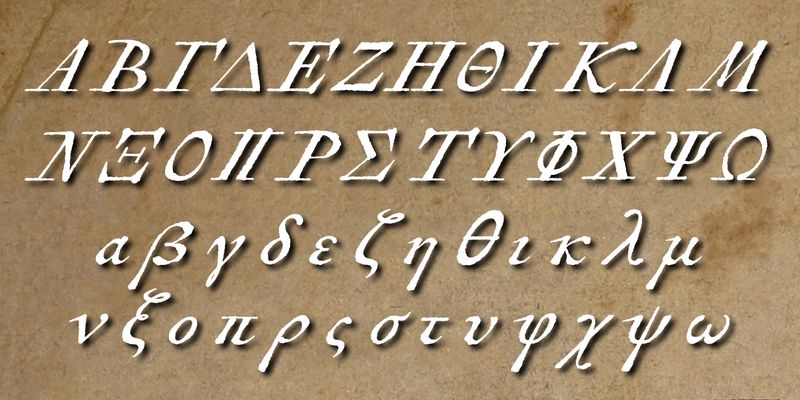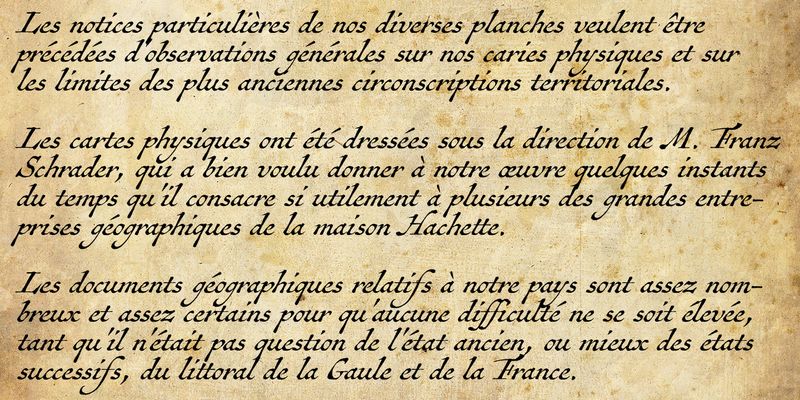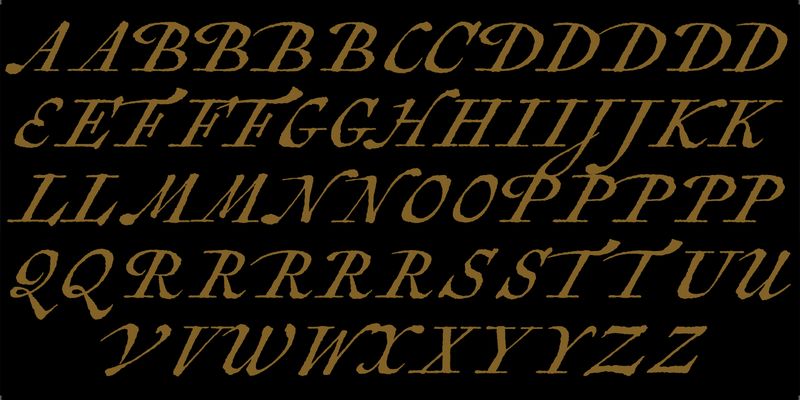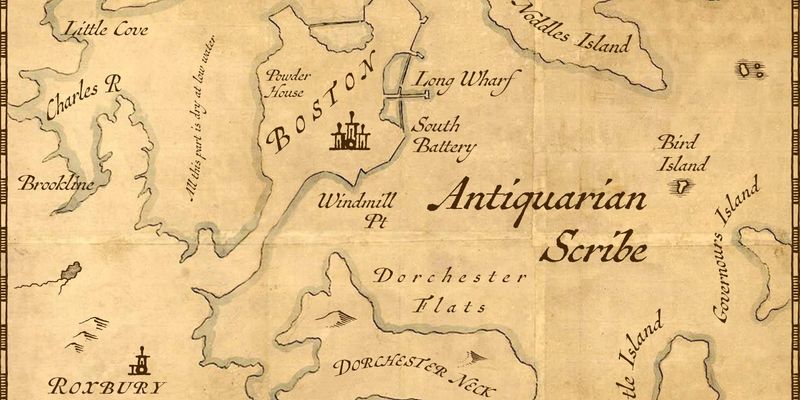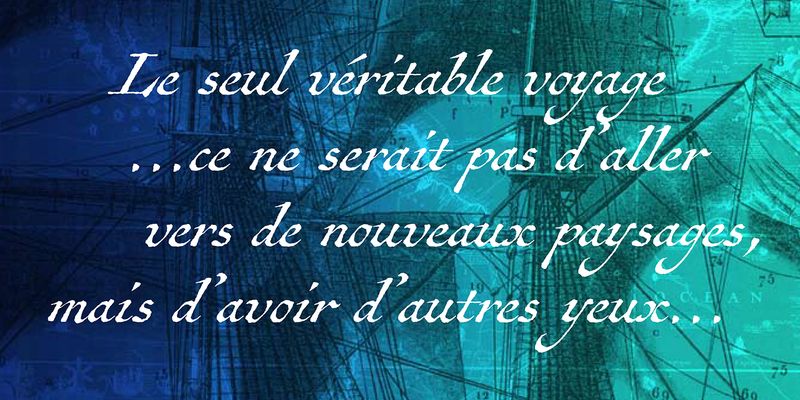
Antiquarian Scribe™ simuliert den handgeschriebenen Text im Atlas Historique von Henri Abraham Chatelain aus dem 18. Verfügt über mehr als 1.000 Glyphen, darunter vollständige lateinische Schriftzeichen und alte kartografische Symbole.